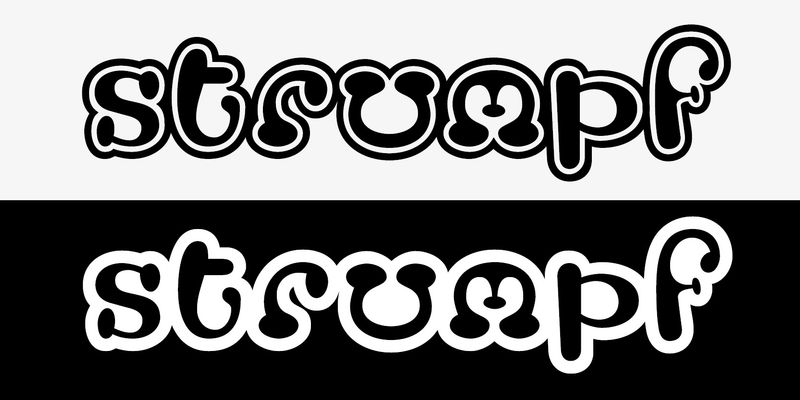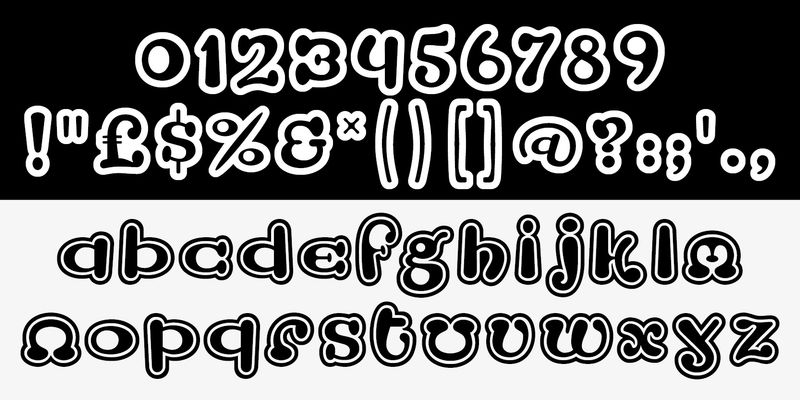
「Strumpf」はポルトガルのデザイナー、Mario Feliciano が作成した書体です。1994 年末、Feliciano は自分の好きなコミックの絵や雰囲気を取り入れた書体の制作に取りかかりました。彼は、このデザインは従来のアルファベットの枠をできる限り打破し、しかも読みやすいものであるべきだと考えました。コミックから得たインスピレーションを忠実に再現した「Strumpf」は、すべての文字が弾けるような個性を持ち、非常に活き活きとしています。一貫性は体系的な文字構造ではなく、丸みを帯びた形とアウトラインが担っています。Open と Contour の 2 つのバリエーションは、それぞれアウトラインの処理が異なりますが、いずれも文字同士が触れることで、その相互作用と陽気な性格がさらに強調されます。長い見出しや本文ではなく、軽快な単語やフレーズを 1 つだけ配置するときに、楽しさいっぱいの「Strumpf」をお使いください。